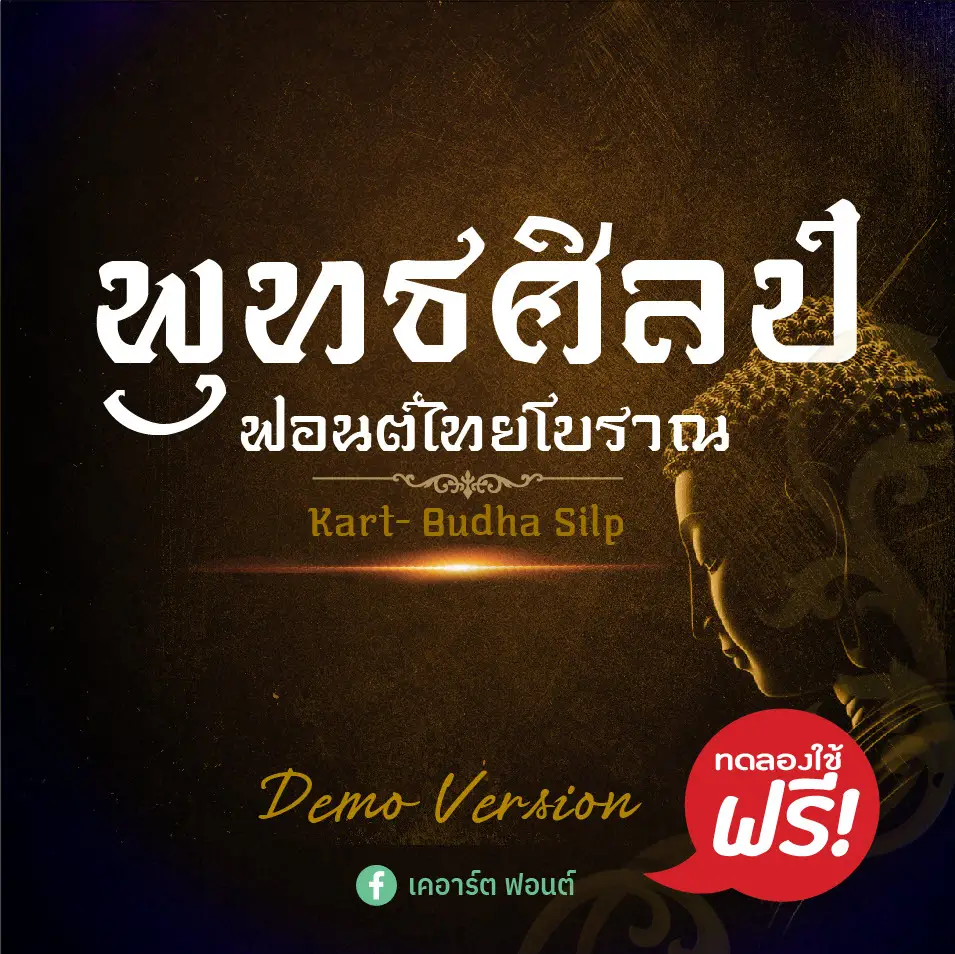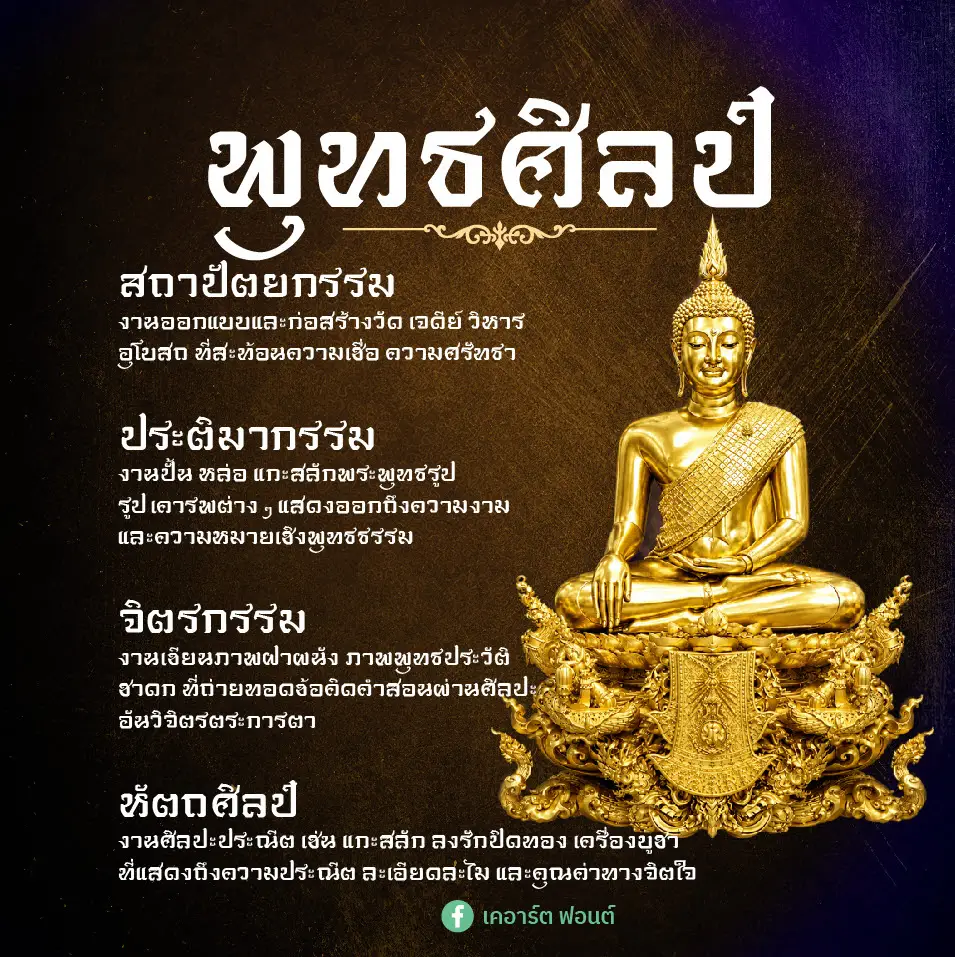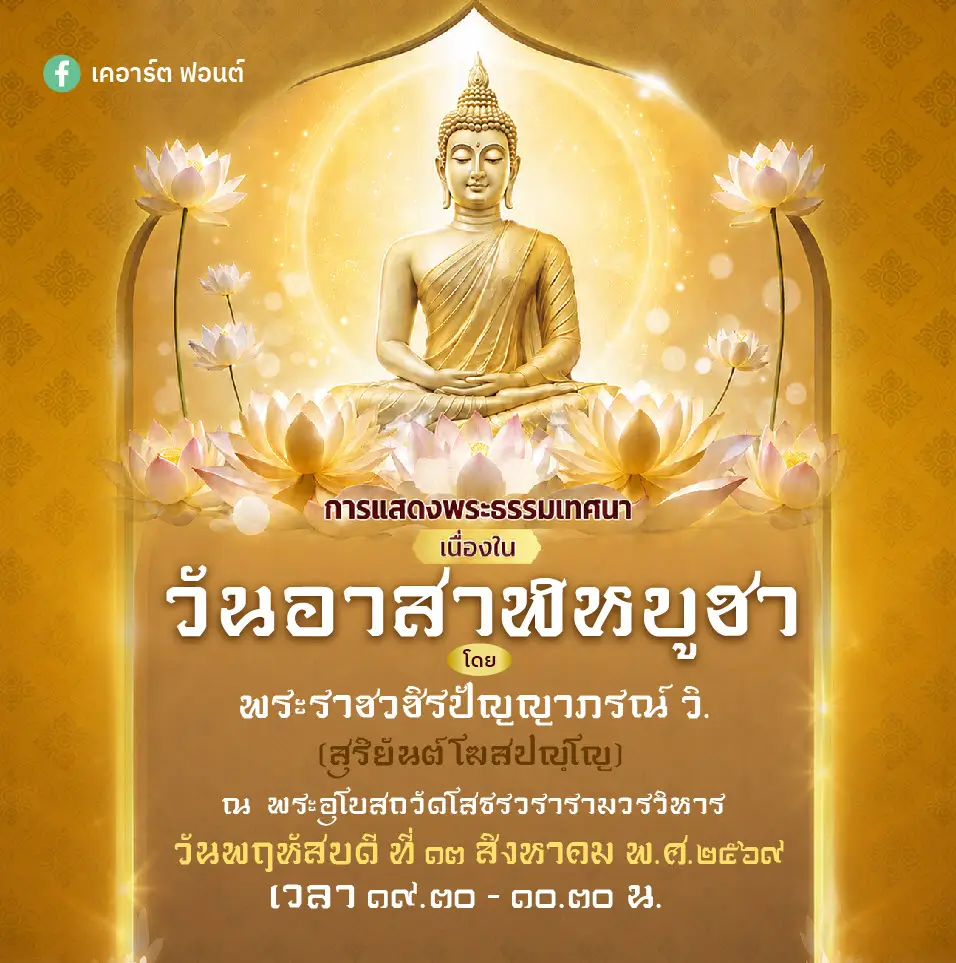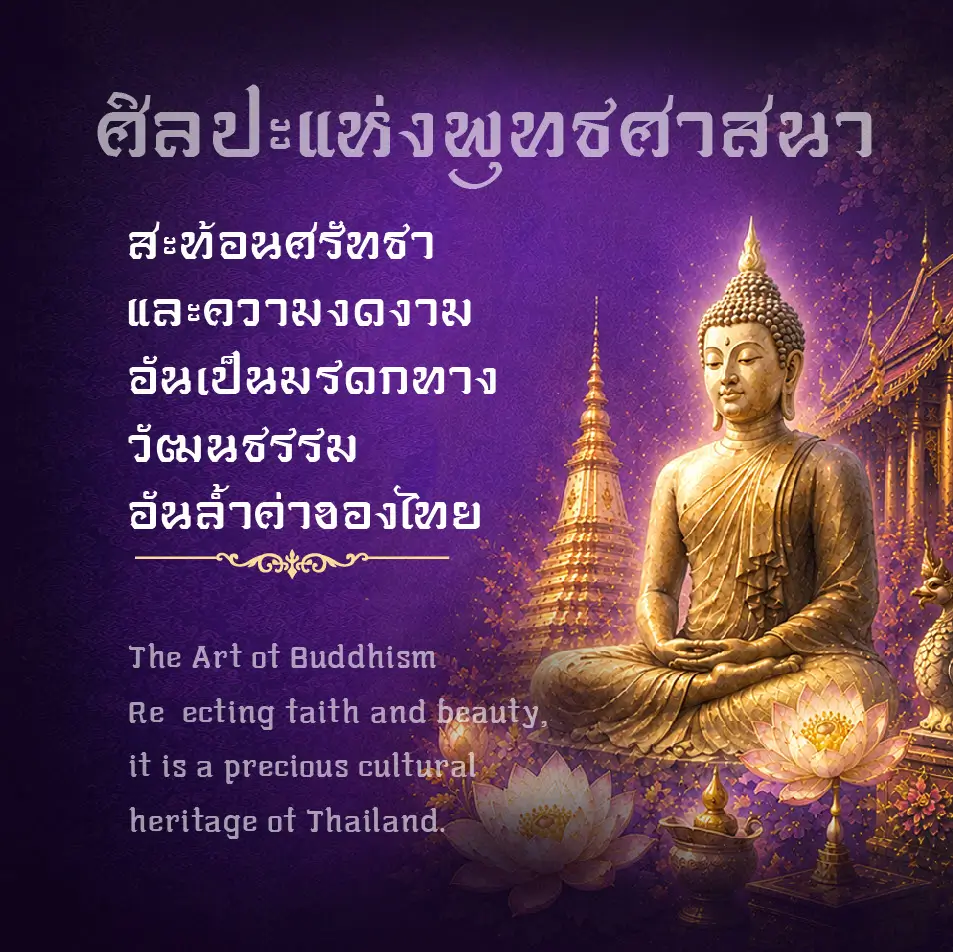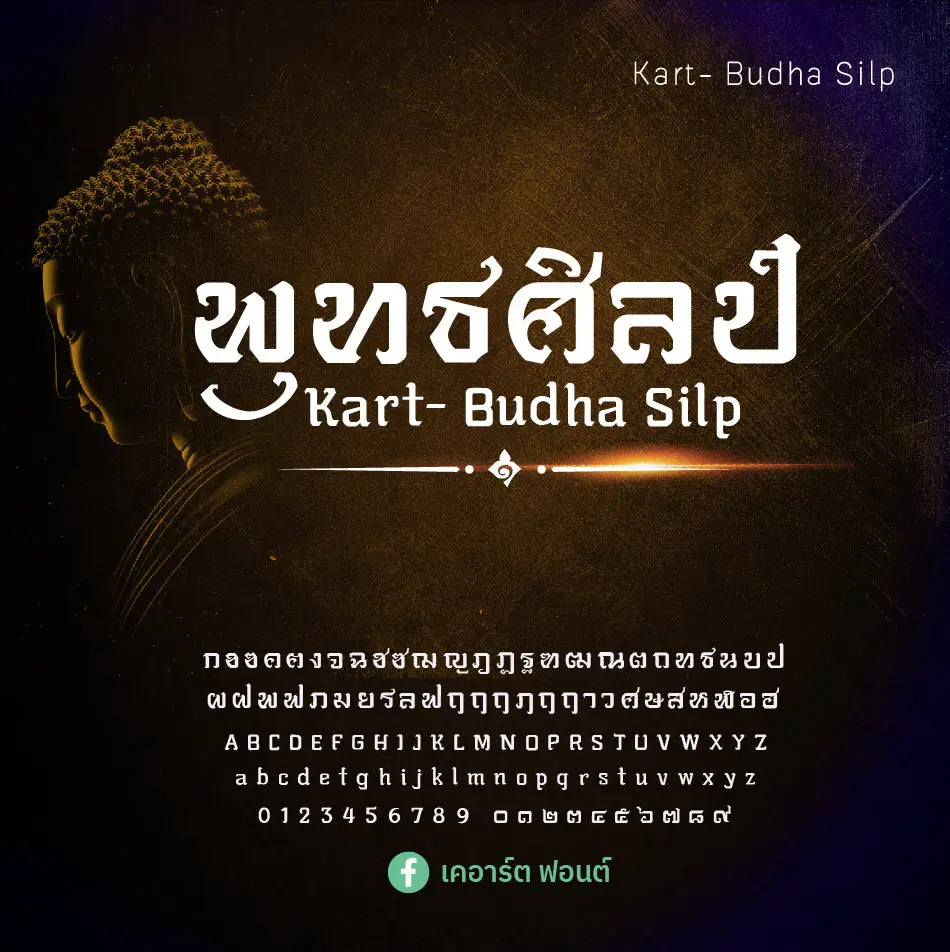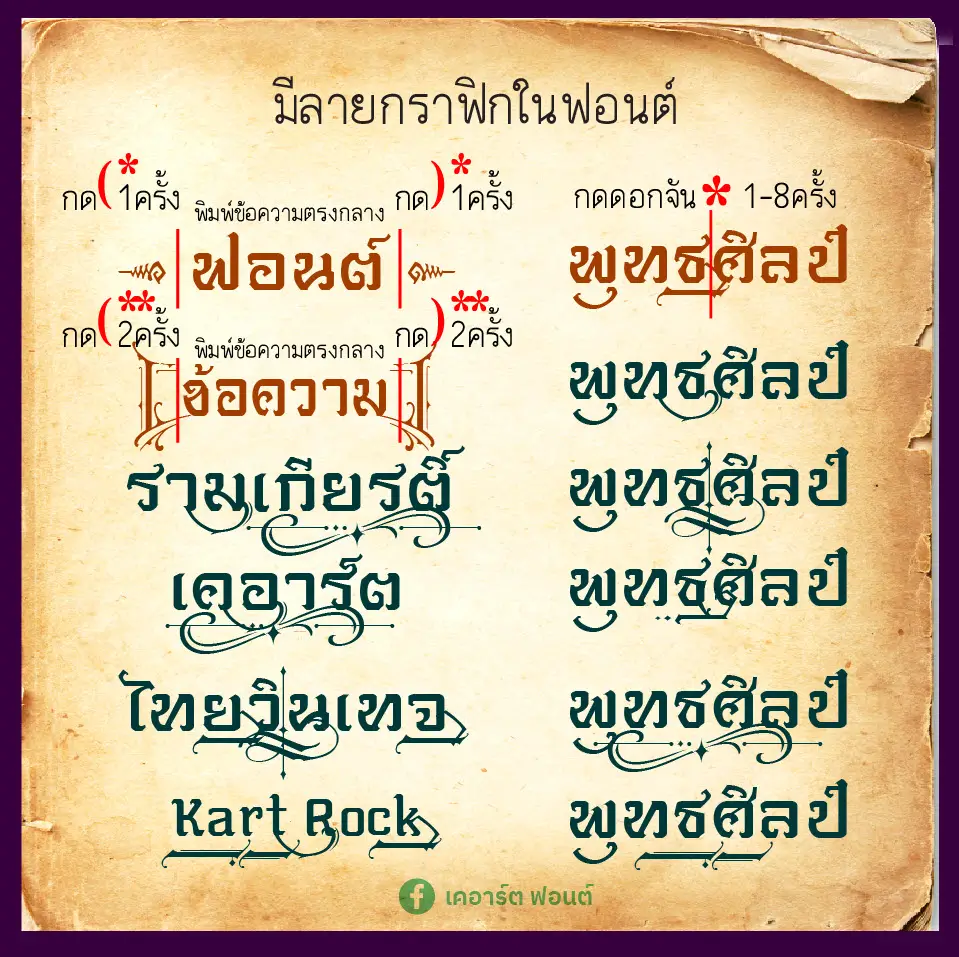
ฟอนต์ เคอาร์ต-พุทธศิลป์ (Kart- Budha Silp) – เป็นฟอนต์ที่เขียนเน้นใช้งานแนว #ฟอนต์พระ #ฟอนต์ไทยโบราณ #ฟอนต์ศาสนาพุทธ #font-thai-boran เป็นฟอนต์ตัวอย่าง (demo) ครับ
เคอาร์ต-พุทธศิลป์ (Kart- Budha Silp)